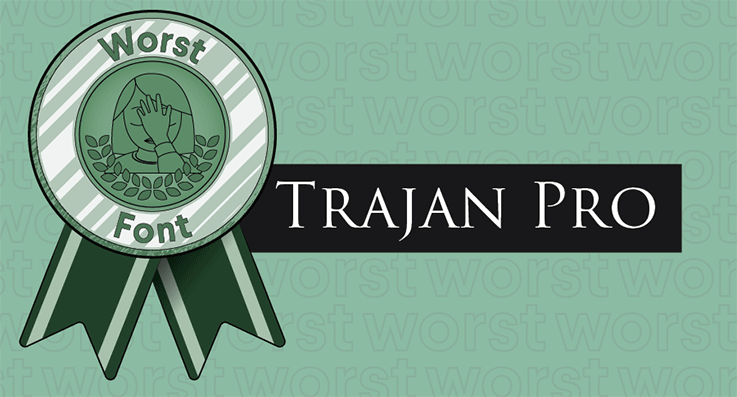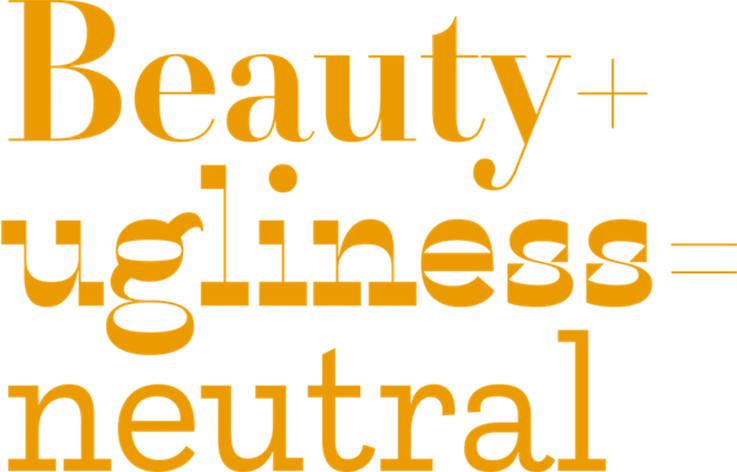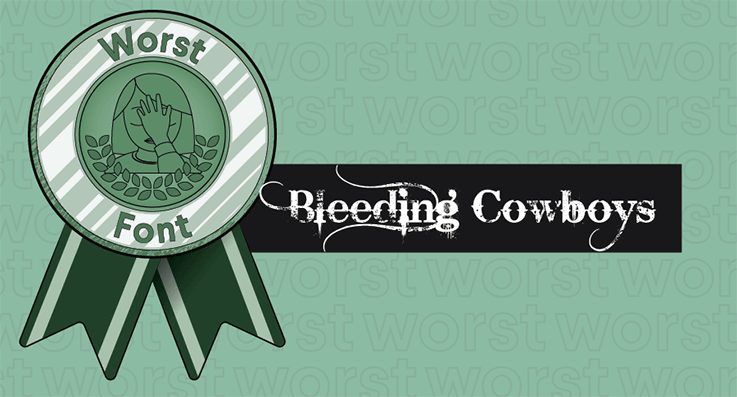
Các quan điểm về font chữ xấu và đẹp
Quan điểm về font chữ xấu và đẹp có thể tùy theo mỗi người có thể đẹp với người này nhưng lại là xấu với người kia, quan trọng hơn trong thiết kế lựa chọn font chữ đẹp nhất chính là nó phù hợp với từng dự án.
Lựa chọn Font chữ là một trong những lựa chọn thiết kế quan trọng nhất để thực hiện khi thiết kế nhận diện thương hiệu của bạn. Khi bạn lựa chọn được một font chữ đẹp thì ấn phẩm của bạn sẽ thấy đẹp hơn và sang trọng hơn như một người bạn gần gũi, nhưng nếu bạn lựa chọn cho mình một font chữ xấu thì tự nhiên nhìn tác phẩm của bạn lạc lõng và xa lạ. Ngày nay với rất nhiều font chữ đã được các nhà thiết kế sẵn và chúng ta chỉ việc tải xuống và sử dụng. Nhưng không phải font chữ nào cũng coi là tốt đẹp cả mà có cả những font chữ đượt đánh giá là xấu với kiểu thiết kế nhàm chán, hoặc đọc không được. Bởi vì nó cũng có những lý do riêng những font chữ ấy được coi là đẹp và một số lại bị coi là xấu và chúng ta hãy cùng tìm hiểu về chúng nha.
Một số font chữ tốt nhất
- Didot
- Bodoni
- Garamond
- Futura
- Helvetica
- Mrs Eaves
- Baskerville
- Akzidenz-Grotesk
- Clarendon
- Gill Sans
- Verdana
- Frutiger
- FF Din
- Proxima Nova
- Uni Sans
Điều gì làm cho một font chữ tốt?
Mặc dù chúng có thể trông rất khác biệt với nhau, nhưng kiểu chữ tốt nhất có rất nhiều điểm giống nhau. Bao gồm các:
- Khoảng các giữa các từ
- Tính nhất quán
- Cân bằng
- Tính dễ đọc
Khoảng các giữa các từ
Khoảng cách giữa các từ nếu gần nhau quá sẽ khó đọc, cách xa nhau quá sẽ thấy rời rạc. Vì vậy yếu tố đầu tiên xét đến font chữ đẹp chính là nó phải đọc được một cách rõ ràng, có tính thẩm mỹ ngay từ khoảng cách giữa các từ và trong tiếng việt thì cũng cần chú ý cả kích thước của các dấu trong câu có hài hòa hay không. Futura và Helvetica là hai ví dụ về font chữ rất dễ đọc bởi vì ngay cả những chữ cái của họ dù đậm hay gầy, sự sắp xếp của chúng mang lại cho người đọc cảm giác về khoảng cách sạch sẽ.
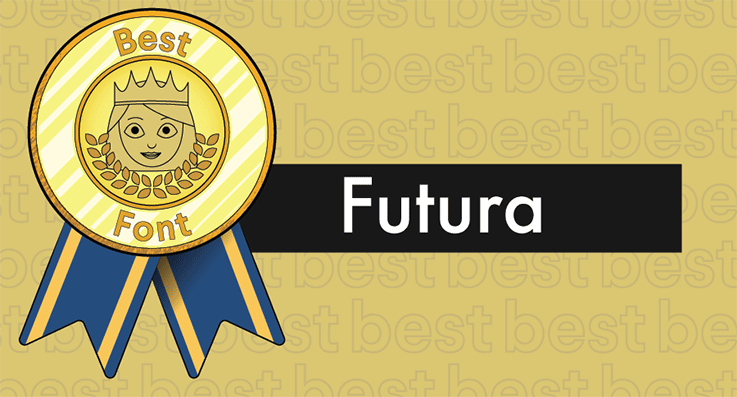
Tính nhất quán
Giữa các chữ cái và các con số hay dấu câu.. đều phải có sự tương đồng và nhất quán với nhau không thể là chữ A có góc nhọn mà kết hợp với chữ B có góc tù được.Tính nhất quán sẽ thể hiện sự chuyên nghiệp và nó còn là nhận diện thương hiệu của công ty trong mọi hoàn cảnh sử dụng.
Tương tự, nếu một font chữ có các chữ cái dày với các góc tròn, mềm mại nhưng kiểu đó không mở rộng đến số hoặc dấu chấm câu, font chữ có cảm giác không nhất quán và thậm chí không đầy đủ.
Font chữ cân bằng
Một sự pha trộn cân bằng giữa dày và mỏng, nặng và nhẹ, là một thành phần quan trọng của một font chữ tốt.
Didot là một font chữ tuyệt vời sử dụng các biến thể mạnh mẽ giữa các nét dày và mỏng trong khi vẫn quản lý để duy trì sự cân bằng. Bodoni là một ví dụ nổi tiếng khác về một font chữ cân bằng với các nét thẳng đứng, chắc chắn và các đường cong và đường cong nhẹ hơn. Serifs của nó thêm một chút tinh tế sang trọng mà cũng cảm thấy như đối trọng giữ các chữ cái thẳng đứng.
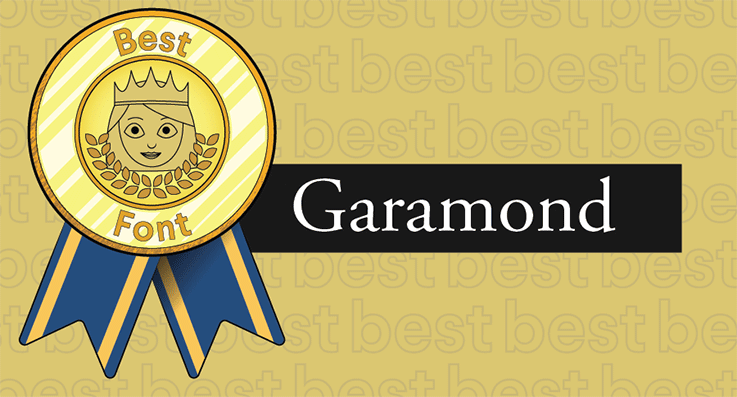
Font chữ dễ đọc
Và cuối cùng, một font chữ phải dễ đọc. phải truyền đạt được thông tin mà bạn muốn gửi gắm một cách nhanh nhất chứ không phải là cách bạn thể hiện “nghệ thuật” mà cuối cùng người đọc nó không hiểu nội dung là gì hoặc quá mất thời gian để đọc và người xem sẽ cảm thấy nhàm chán và bỏ qua. Để kiểm tra xem một font chữ dễ đọc hay không bạn có thể viết nhiều loại từ trong đó, đảm bảo bạn sử dụng mọi chữ cái và một loạt các kết hợp chữ cái khác nhau. Bạn có thể viết nó ra với văn bản nhỏ và kiểm tra chúng
Các font chữ đã đứng trước thử thách của thời gian, như Garhua, vẫn được các nhà thiết kế ưa chuộng vì chúng dễ đọc ở nhiều kích cỡ, màu sắc và bố cục khác nhau. Sans serifs đặc biệt tốt trong việc duy trì mức độ dễ đọc bất kể bối cảnh: do đó độ bền của các font chữ như Helvetica .
Bên cạnh những font chữ được coi là đẹp thì cũng có một số font chữ tồi tệ nhất
- Copperplate Gothic
- Times New Roman
- Trajan Pro
- Comic Sans
- Courier
- Papyrus
- Bonzai
- Neuland-Inline
- Brush Script
- Souvenir
- FF Blur
- Impact
- Trajan Pro
- Curlz
- Jokerman
- Lobster
- Bleeding Cowboys
- Arial
Điều gì làm cho một font chữ xấu?
Có rất nhiều cách để coi một font chữ có thể xấu chứ không phải do chúng không đẹp về mặt thẩm mỹ. Những font ấy có thể nó đẹp về thẩm mỹ nhưng chúng đã được sử dụng quá nhiều đến mức nhàm chán mất tinh sáng tạo và không còn phù hợp với xu hướng hiện đại ngày nay vẫn được coi là font chữ xấu xí và có những font chữ xấu xí bởi nó quá rối rắm mất cân bằng cũng như không thể đọc nổi và sau đây là một số những yếu tố gây nên font chữ xấu